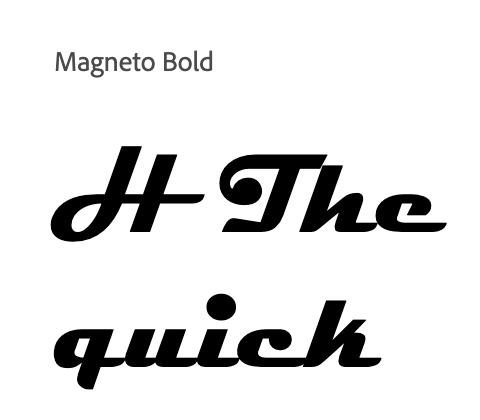
Font aus einem Bild-Icon gesucht
ich bin auf der Suche nach dem Namen der Schriftart, die im beigefügten Bild zu sehen ist. Leider habe ich keine weiteren Informationen dazu. Eine Recherche anhand des Bildes hat bisher keine Ergebnisse geliefert. Der linke untere Teil der Schriftart ist abgerundet, was ich noch feststellen konnte. Hat jemand eine Ahnung, um welche Schriftart es sich handeln könnte? Es sollte idealerweise keine Alternative sein, es sei denn, sie ist der Originalschrift sehr ähnlich.